Шрифт для вишивки хрестом метрики
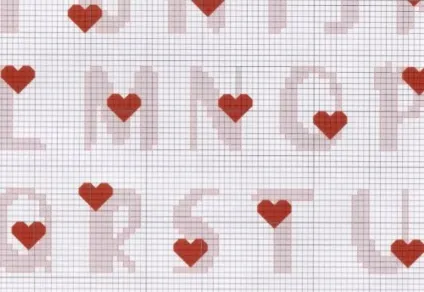
Що таке метрика?
Як вам подобаються черепашки, що зображують вимірювання ваги, часу і зростання?
На мій погляд, це оригінальне і веселе відкладення пам'ятного моменту.
Буває, що вишивають лелеки, що приносить немовля, іноді вишивають ліжечко з іграшкою, що чекають свого господаря або господиню. Часом вишивають ступні або ручки, ведмедиків, зайчиків, квіти або навіть клумбу! Є багато різних схем, придатних для новонароджених. Досвідчені вишивальниці йдуть на хитрість, коли невідомо, хто народиться - хлопчик чи дівчинка. В такому випадку метрика вишивається заздалегідь, а написи - вже в останній момент, коли все стає відомим. Коли невідомий стать дитини, то вибирають схему без статевої приналежності, наприклад, малюка з пляшкою або в капусті, як на малюнку нижче:
Ось ще варіант, як можна зробити вишивку «для всіх»:
А ви в курсі, що означає для вишивальниці ангел? І якої події потрібно очікувати після такої роботи?
Крім того, існує безліч «універсальних» схем. Це такі схеми, які підходять і хлопчикам, і дівчаткам. Їх відмінність полягає в кольорі. Наприклад, можна вишити коляску. Якщо очікується хлопчик, то вона вишивається в «хлоп'ячих» тонах, а якщо дівчинка - то в «дівчачих». Ось один з таких прикладів:
Капюшон коляски, стрічку і ковдру можна забарвити в потрібний для випадку колір.
Все про шрифтах
Для підписання метрики використовують шрифти. Що це таке? Це набір букв і цифр, що відрізняється одним розміром і стилем. Шрифти бувають різні - прості, фігурні, похилі, з квітковими елементами і багато інших.
Колір нитки вибирається залежно від того, хто народиться. Для хлопчика вибирають блакитні, сині, сірі тони, для дівчинки - рожеві, червоні і їх відтінки.
Розташування написів
Даний пункт є індивідуальним для кожної вишивки. Перед початком роботи потрібно визначити, в якому місці буде напис, розрахувати місце, яке вона буде займати. Припустимо, вишивка розташовується зліва і внизу - в такому випадку метрика повинна бути справа.
Якщо ж зшита малюнок займає велику площу, як в вищепоказане прикладі з коляскою, то напис може розташовуватися як знизу, так і зверху. Головне, щоб була гармонія в картині.
приклади шрифтів
Тепер розберемо на прикладах, які шрифти бувають, і для яких новонароджених вони підходять.
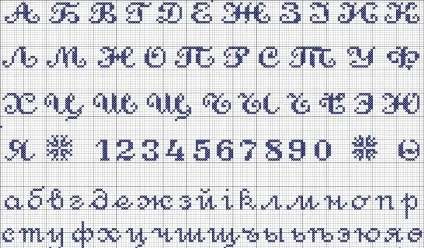
Такий шрифт зручно відшивати - він простий, його легко вирахувати по клітинам. Він підходить для всіх випадків. Так як маленькі букви займають трохи клітин, то ними можна відшити довге ім'я.
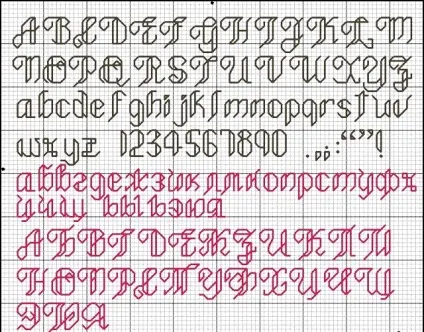
Даний вид шрифту вишивається за допомогою бекстіча. Не всі вишивальниці його люблять. Я б порадила такий спосіб застосувати для «Мальчуковой» записи.
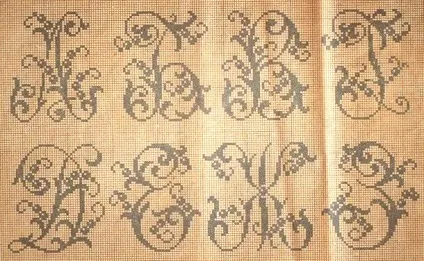
Подібні букви підійшли б для дівчинки. Уявіть, як гарно виглядало б ім'я, написане ними!
Якщо ви досвідчена майстриня, то можете використовувати більш складні елементи:
На розшивку таких букв буде потрібно більше часу. Однак результат буде дуже гарним!
Не менш складним і витонченим виглядає такий шрифт, хоча для вишивки він елементарний:
Я розповідала вам, що букви бувають похилими. Вони також можуть бути простими і складними. Останні мають елементами прикраси - квітами та іншими.
Вище я показала «складний» шрифт. А ось - простий і похилий:
Він Готується швидко, легко розрахувати необхідну кількість клітин.
Підбиття підсумків
Який би шрифт ви не вибрали, у вас буде унікальна напис і робота, яка більше не зустрінеться ніде! Такий подарунок буде зберігатися все життя.